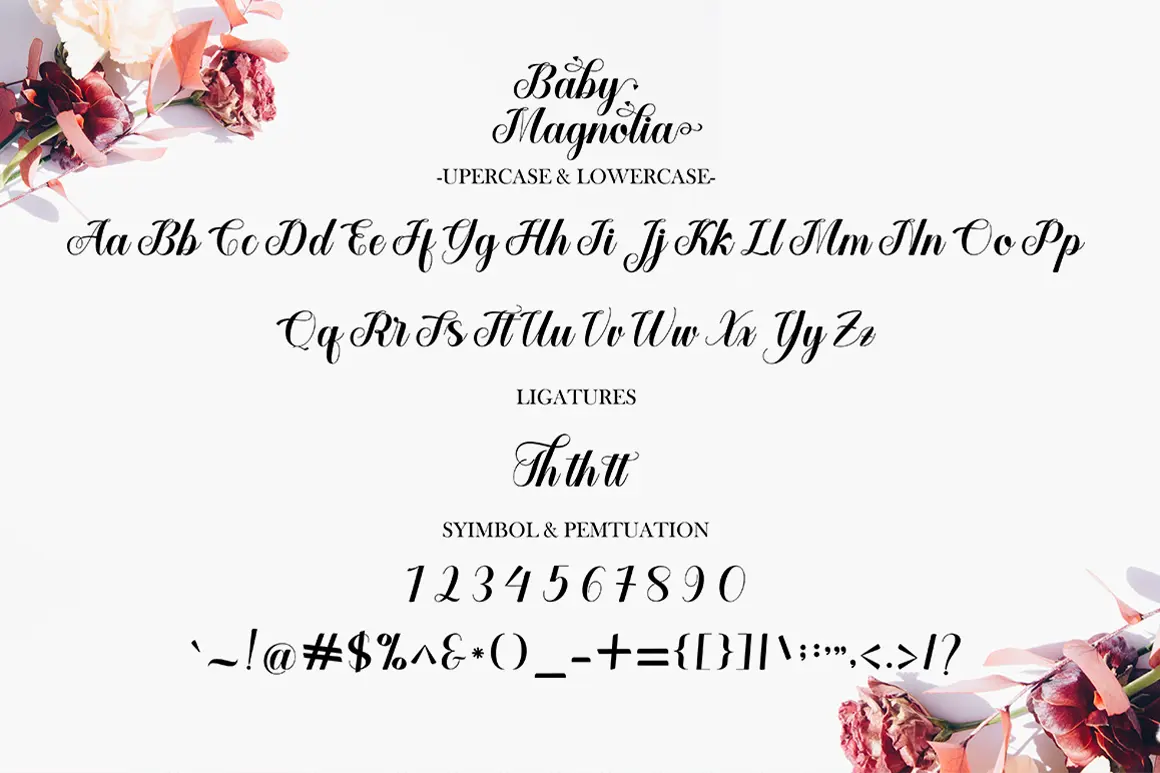
فونت دستنویس Baby Magnolia
Baby Magnolia یک فونت ظریف، متفاوت و روان است که با استایل دستنویس خود، حس لطافت، لطیفنگاری و خلاقیت بصری را به طرحهای شما میآورد. این فونت کاملاً برای پروژههایی که نیاز به ظرافت و روح خلاقانه دارند، ایدهآل است؛ از طراحی کارت دعوت گرفته تا برندینگهای خاص.
💡 ویژگیهای کلیدی
- استایل دستنویس با حرکتهای نرم و پیوسته
- PUA Encoded – دسترسی آسان به تمامی گلیفها و خطوط زینتی (Swashes)
- خوانا، خاص و قابل استفاده در پروژههای دیجیتال و چاپی
- مناسب برای طراحی لوگو، نقلقولهای تزئینی، کارتهای عروسی، محصولات شخصیسازیشده